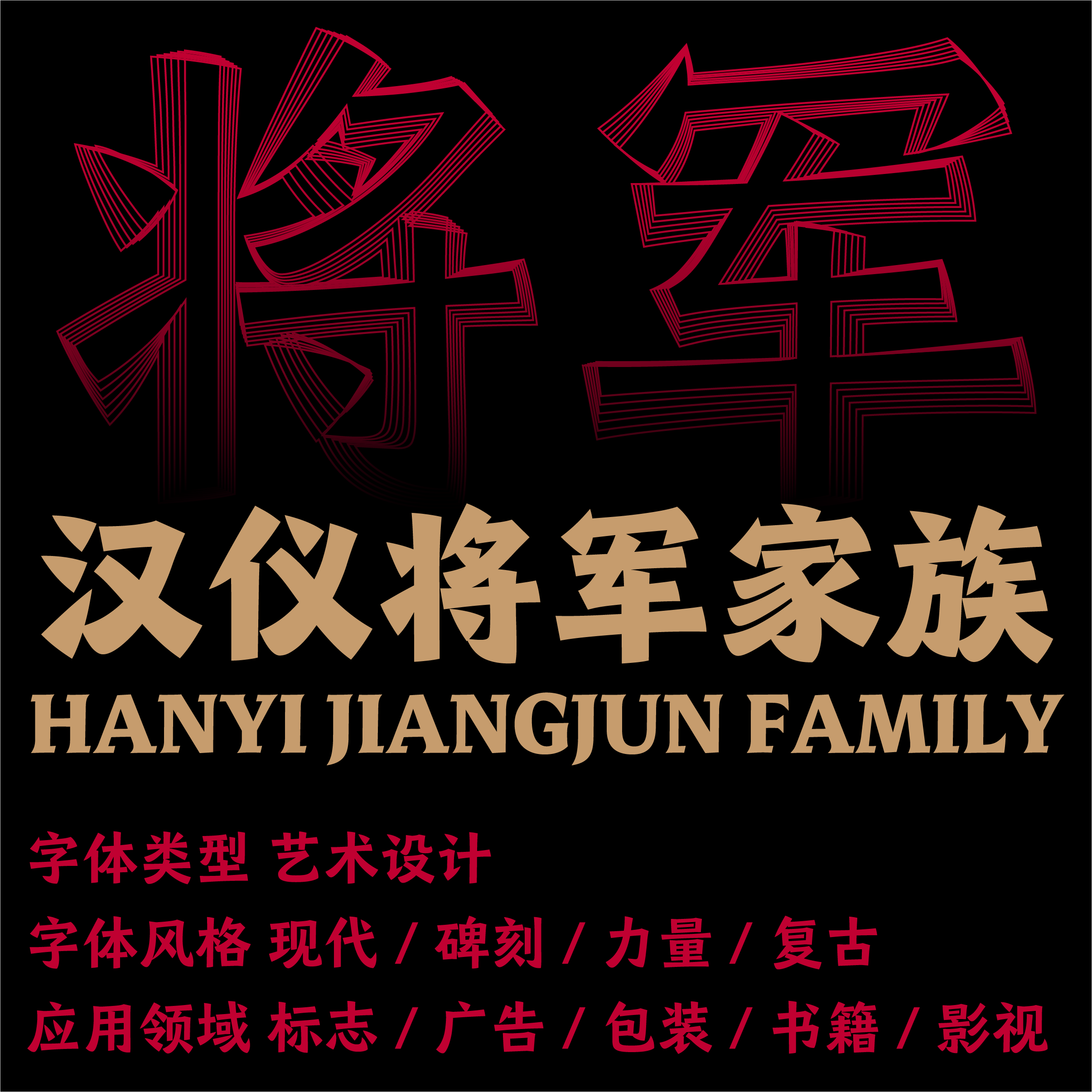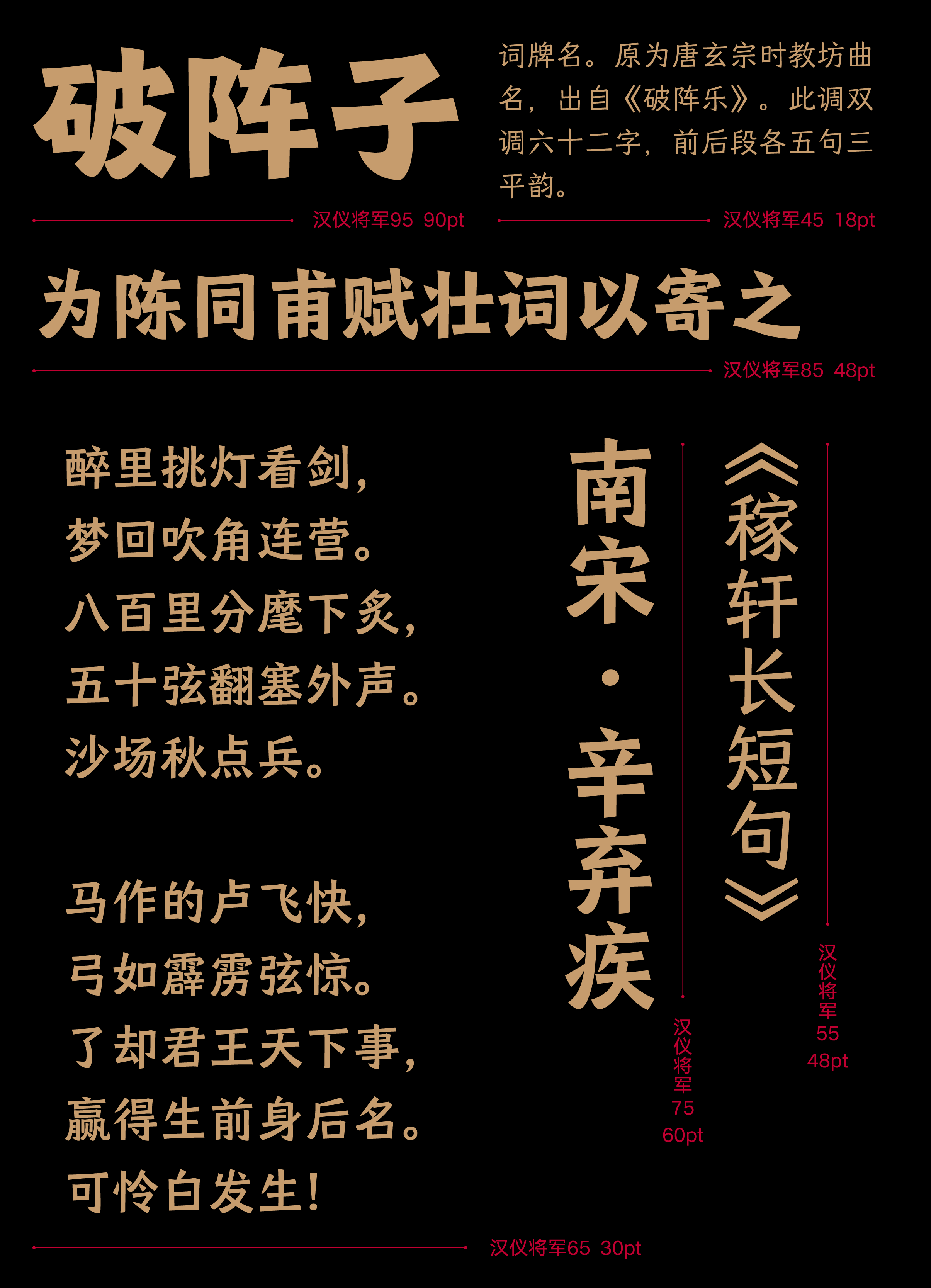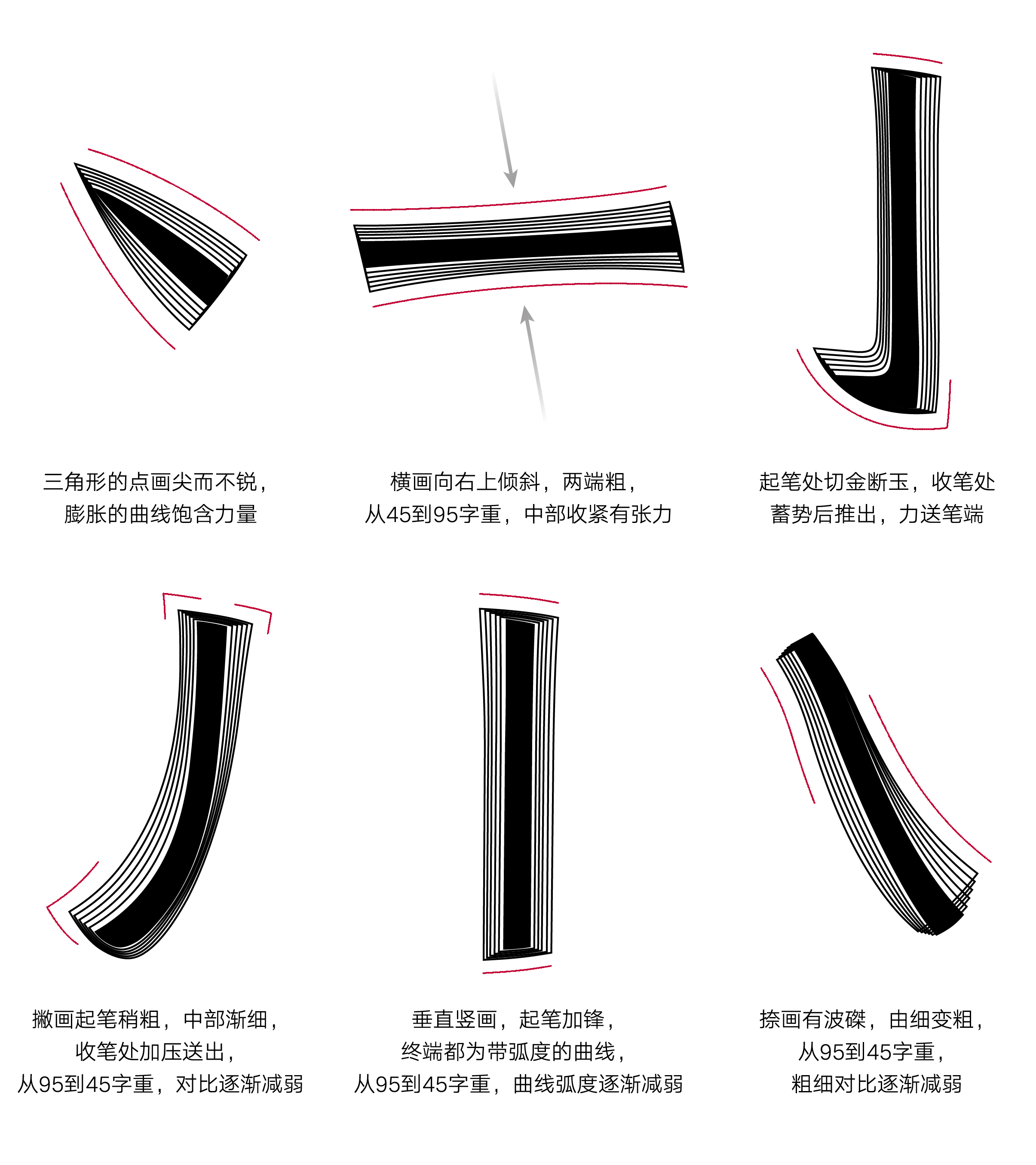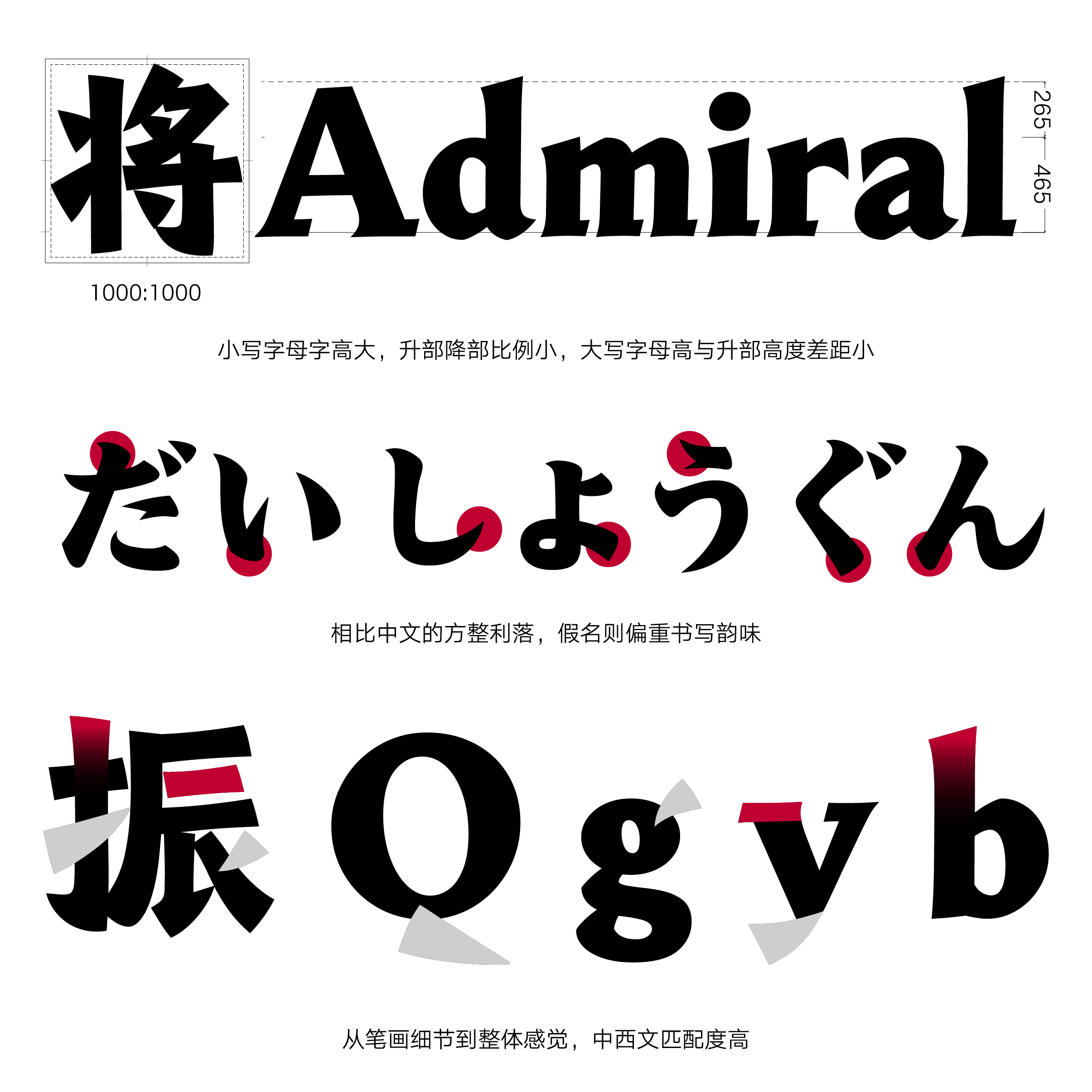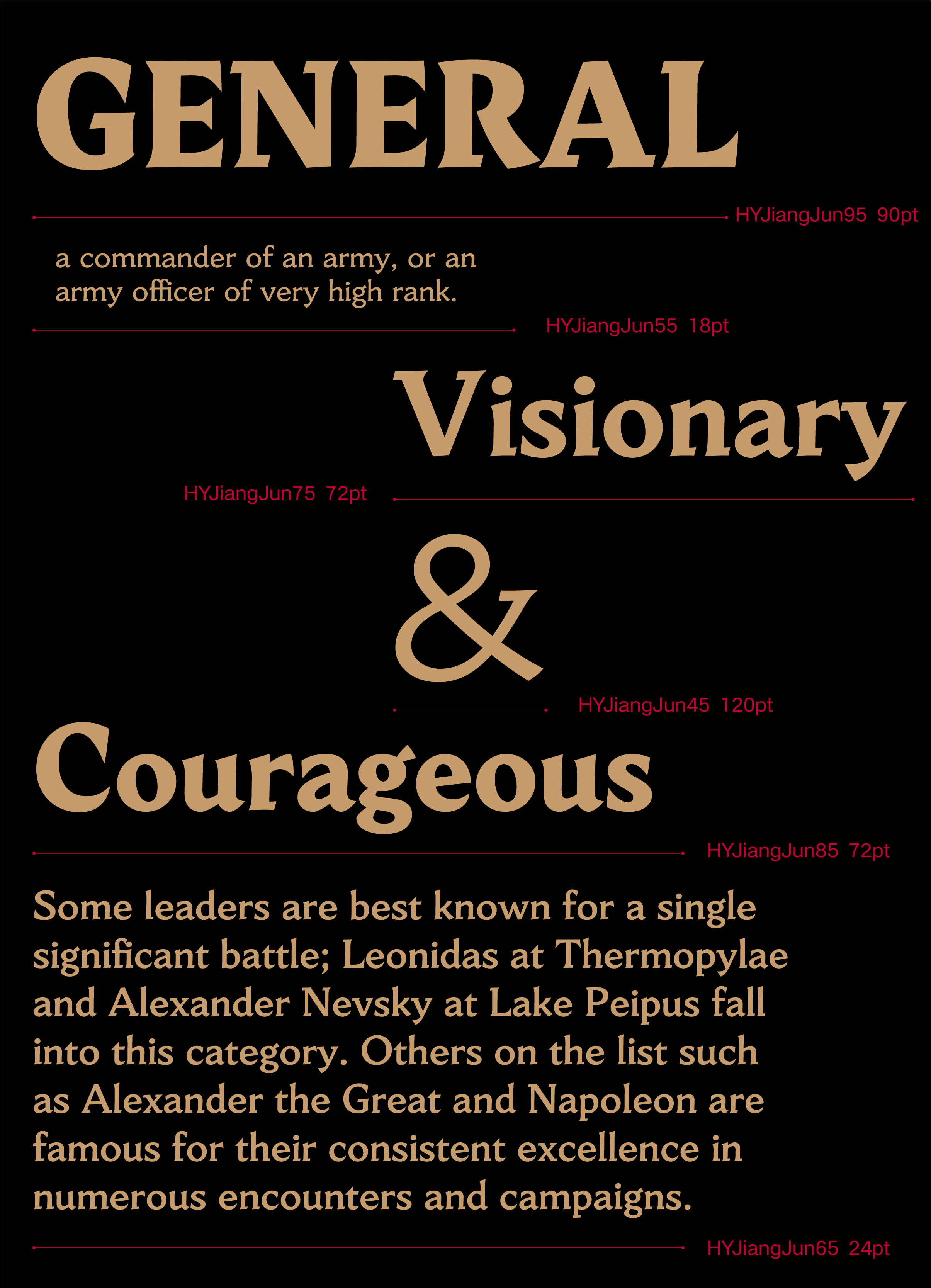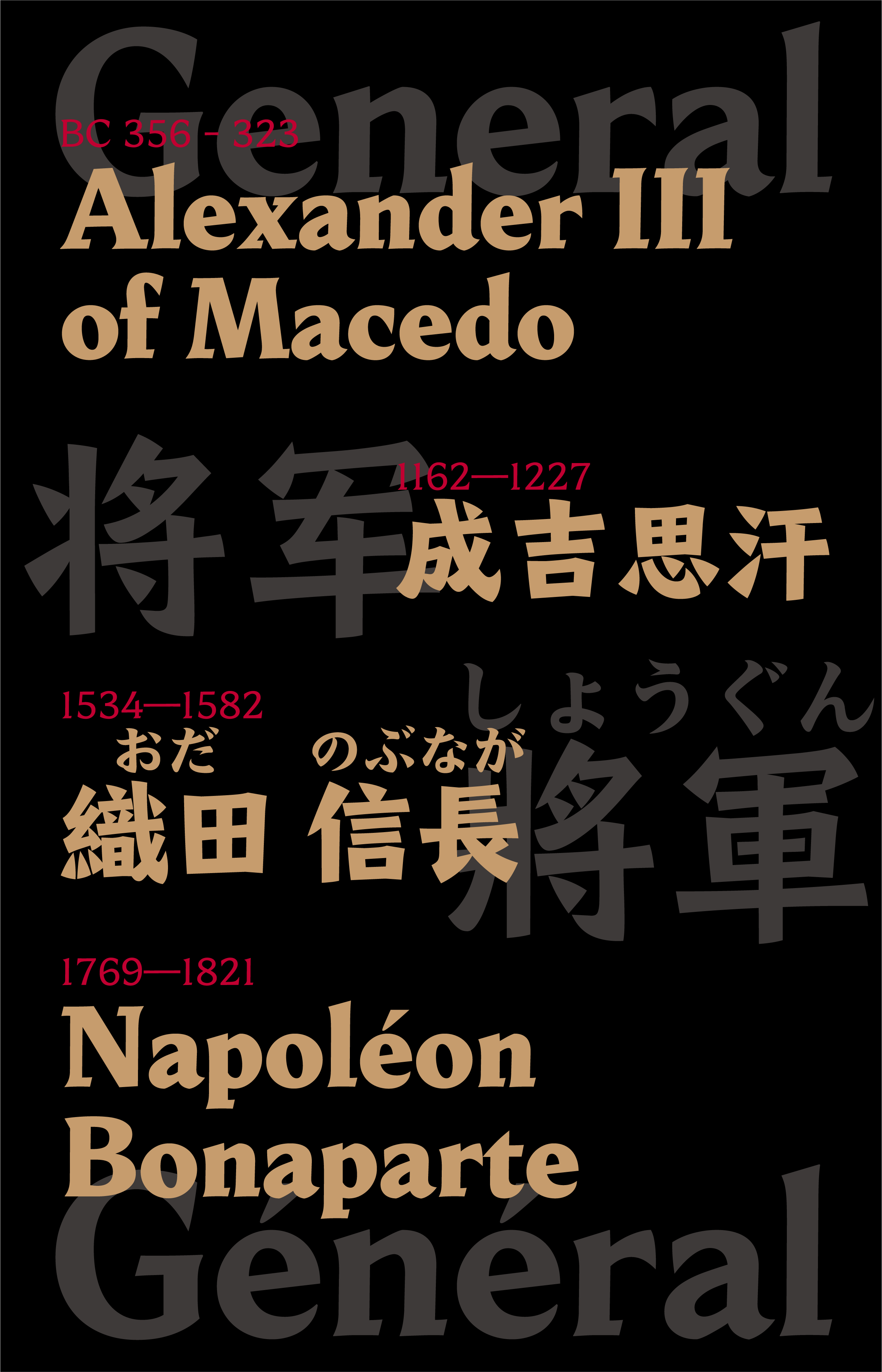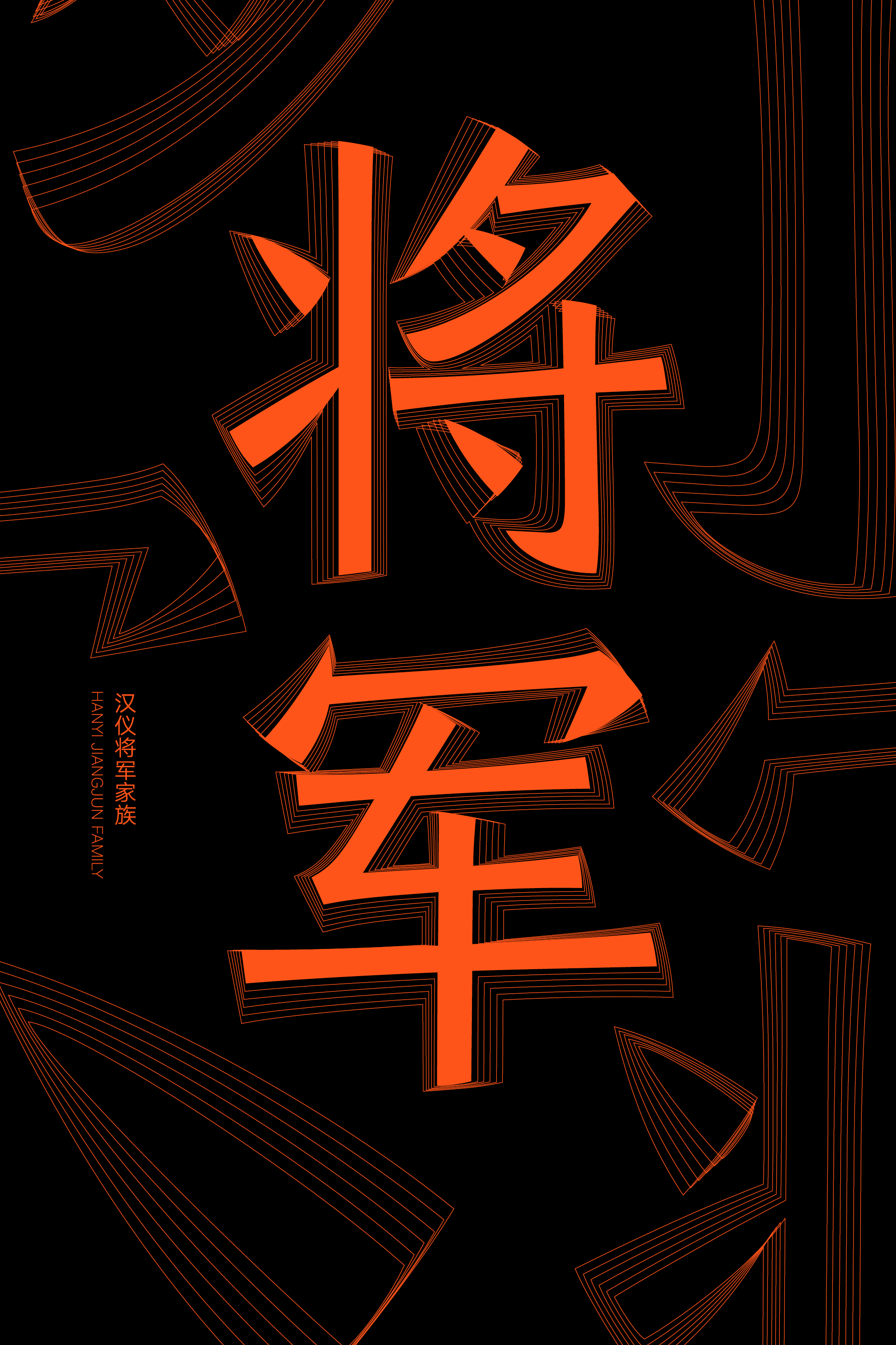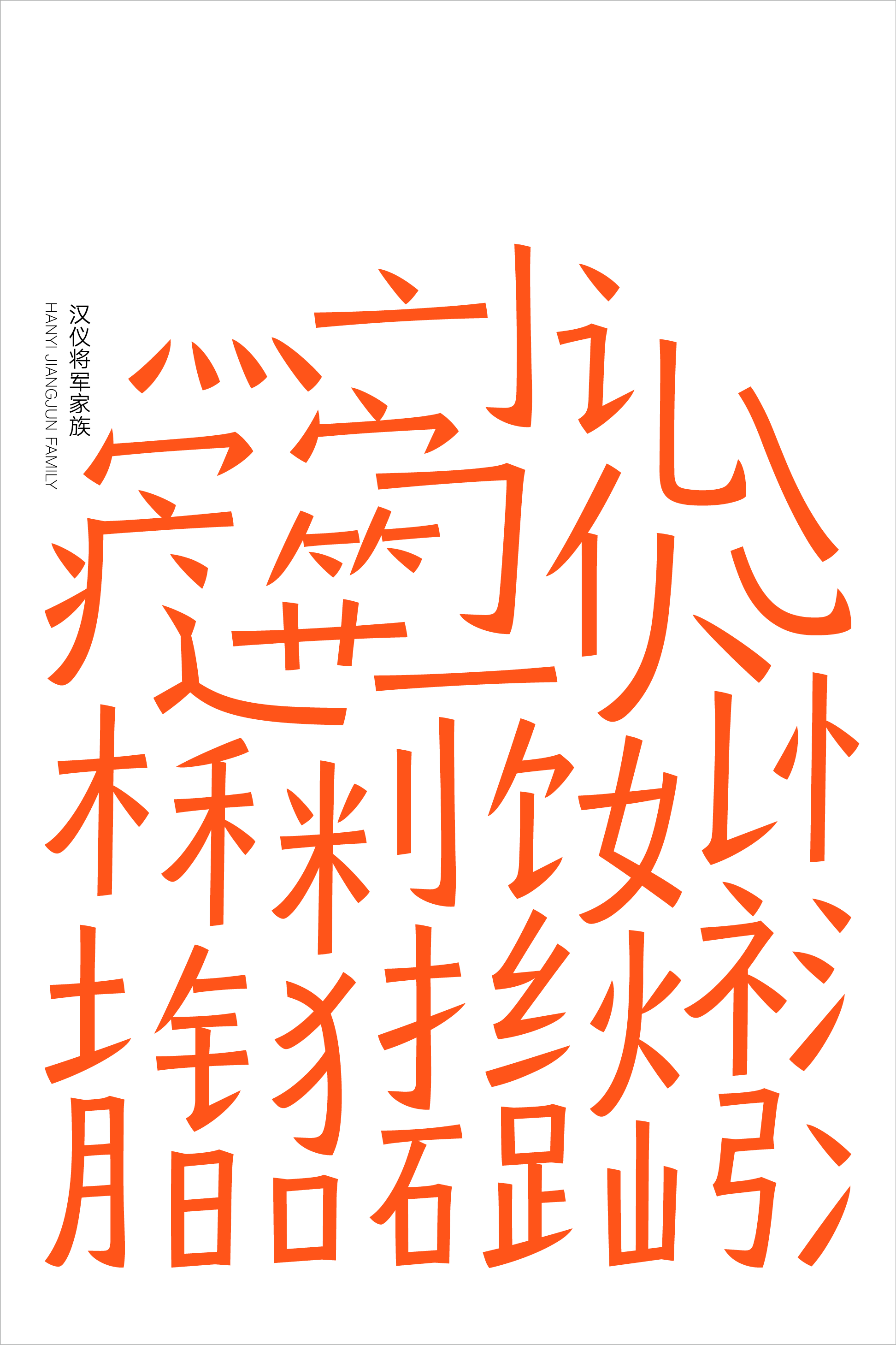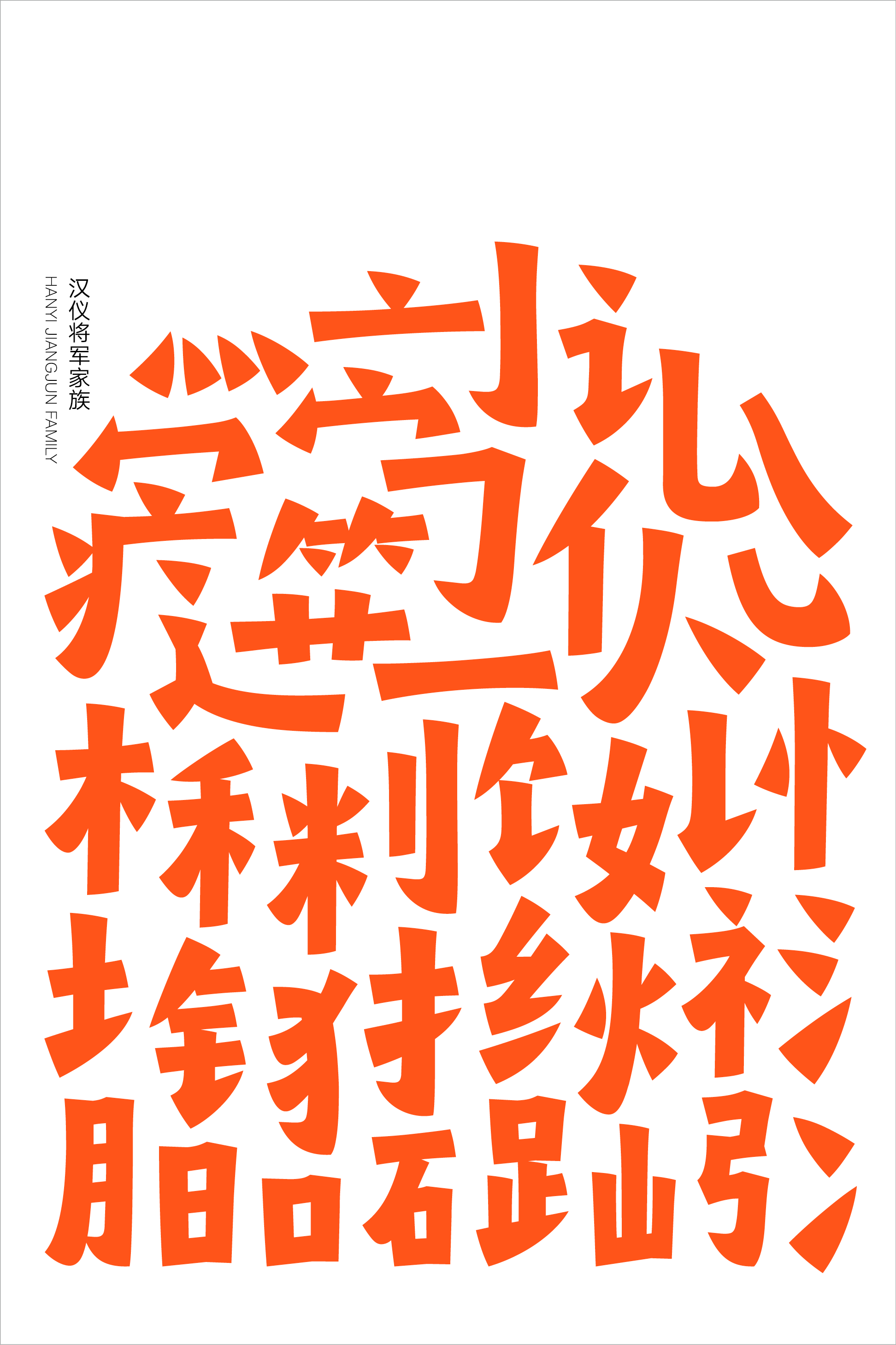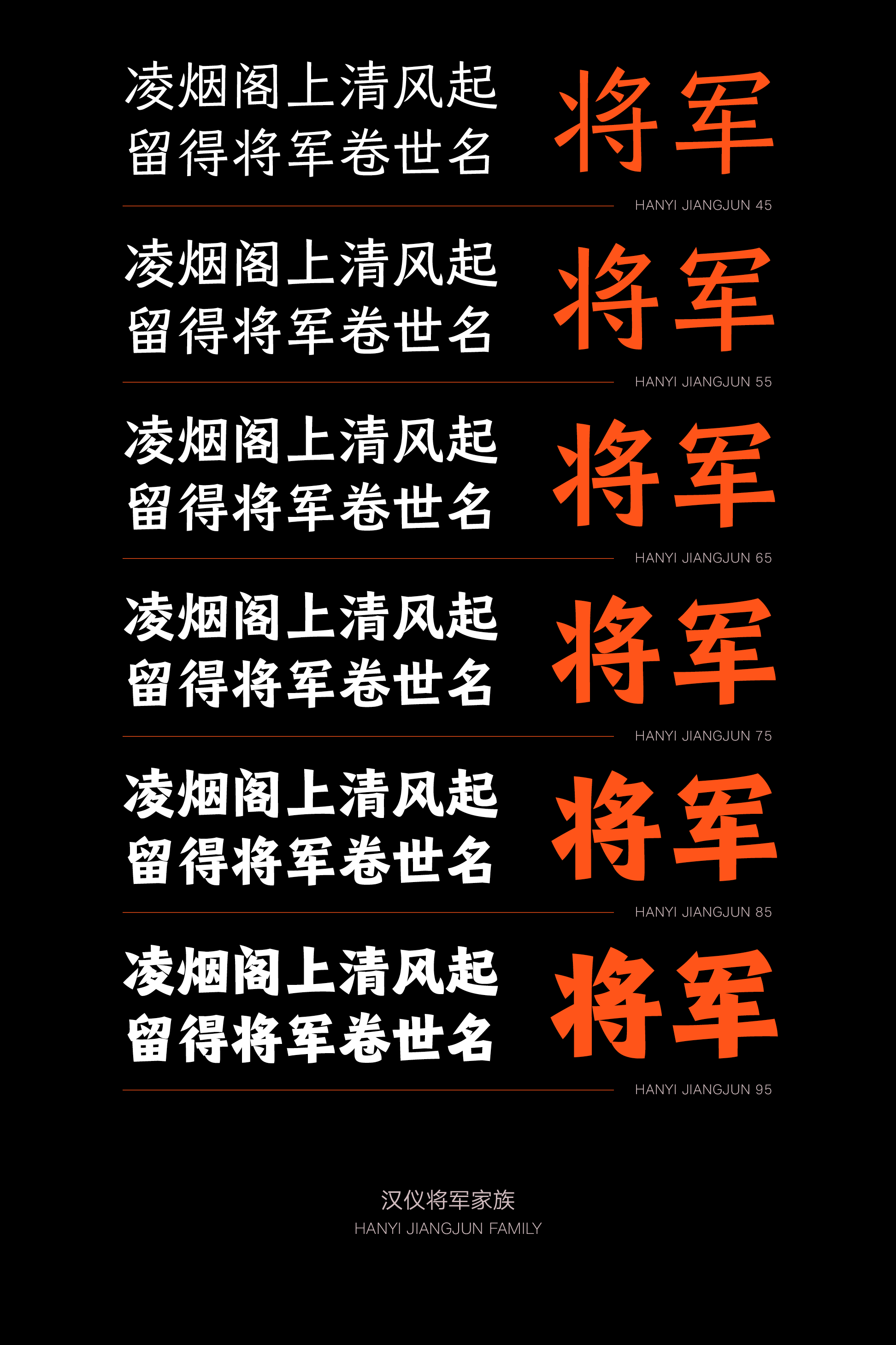
汉仪将军
汉仪将军 | 整体特点
汉仪将军是一款具有碑刻味道,力量爆棚,饱含传统基因和现代设计手段的标题属性用字。相比中文的方整利落,假名则偏重书写韵味,西文部分也因为书写工具的不同而不同。正是因为这些细节的和而不同,在应用时会更加强化标题属性用字。汉仪将军就好像一位“将军”,英姿飒爽、胜券在握,助力品牌征战四方,所向披靡。
2023年,汉仪将军拓展成为45到95共计6个字重的家族,延续了原汉仪将军(现汉仪将军95)的设计风格,简洁爽利,昆刀断玉。从标题属性到正文属性,这位“将军”在不同的应用场景中随机应变,战无不胜。
汉仪将军|字形特点
汉仪将军的字形方正现代,字如其名般有着力拔山河气盖世的将军气质。重心稍低更显稳重,中宫宽绰、字形挺拔。
笔画外拓,结构散朗雄强,又扩大了字内空间。
蕴含三角构成和圆形构成,这些几何特征让字体现代时尚。
汉仪将军 | 笔画特点
汉仪将军笔画干净利落,饱满厚重,方圆兼收,有几何意趣。
点画多为视觉上对称,带有几何风格的三角形。 与竖钩、短撇、平撇相呼应,稳重中带有动态。
竖提、竖钩、竖弯钩、戈钩、卧钩笔画统一和谐,起笔略粗,行笔变细,收笔处顿笔,尖角出笔。
框形结构中,视觉上横画被包含在折笔与搭接处。丰富了线条和结构的变化,细节精致,贴合传统书法笔画搭接审美。
竖折分为两种:直竖直接翻折;斜竖带笔切锋翻折。
对于竖折的细节处理,独体字和上下结构的字,起笔加峰,左右结构的字起笔不加锋,加大字内空白空间。
断开、错落的用笔,让字体更现代,同时避免笔画连接处过于粗重。
根据字形结构和空间大小的需要对字体细节进行调整。笔画既有视觉上的延展性,又使空间分布更合理。
汉仪将军 | 中西文匹配
汉仪将军的西文是有粗壮几何形态的衬线字体。小写字母字高大,升部降部短。从笔画细节到整体气质以及排版上看,中西文匹配度都极高。小写字母斜切入笔,起端略粗,既符合传统西文书法写法,又与中文起笔加锋和谐统一。
大小写字母的衬线都是一边是粗壮衬线,一边是尖角。比起整体都是粗重衬线的字体更灵动又增大了字体间的空间。
修正“X”视错觉,断开第二笔。字母下半部分空间变大,重心提高同时减少了笔画交接处的重量。第二笔设计的更细,入笔、出笔有西文书法书写的韵味,与中文的书写感相匹配。
字母终端大小、方向根据字母空白空间大小不同而有差异调整,终端有直线、曲线和尖角。
汉仪将军 | 设计团队
汉仪将军 | 字体样张